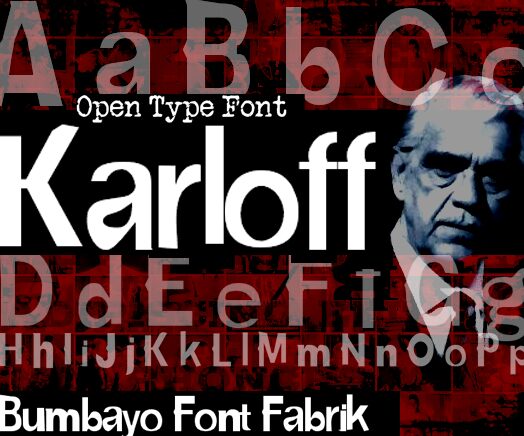
Karloff von Digital Dog Graphics ist eine kostenlose Horror-Display-Schrift, die aussieht, als wäre sie aus schwarzem, morschem Holz gehauen. Jeder Buchstabe wirkt wie gesplittert und zerrissen, mit rauen, unebenen Kanten, die wie dickflüssige, geronnene Tinte auf dem Papier zusammenlaufen. Das Ergebnis ist eine schwere, bedrückende Textur, die sofort für eine unheimliche B-Movie-Horror-Stimmung sorgt, ganz ohne zusätzliche Grafiken.
Mit Karloff ziehen deine Überschriften die Blicke auf sich wie ein altes Drive-in-Horrorplakat – laut, kantig und ein wenig wahnsinnig. Diese kostenlose Schrift eignet sich hervorragend für Halloween-Flyer, Beschilderungen für Geisterbahnen, Key-Art für Horrorfilme, Spieltitel, gruselige YouTube-Thumbnails sowie unheimliche Buch- oder Zine-Cover. Kombiniere sie in kleinen Größen mit einer klaren, schmalen serifenlosen Schrift für den Fließtext, damit die wilden Formen von Karloff voll zur Geltung kommen.
Präsentation und Schriftprobe von Karloff
Zeichentabelle der Schriftart Karloff
Zeichentabelle von Karloff: Basis-Lateinisch, Seite 1
Glyphen der Schriftart Karloff — Basis-Lateinisch, Seite 1